字体设计,没想到你以前这么骚!
在我的文章中,与大家分享了汉字字体的发展过程,因为篇幅等原因,对于印刷字体只是讲到了宋体与黑体的部分,之后的发展并没有再叙说。今天,不妨继续来填填坑。我们知道,在民国时期,就出现了大量的美术字体,它们有的是宋体与黑体的变体,有的充满装饰韵味,自成一派。可以说,这些美术字与我们如今的字体设计有着莫大的关系,那么今天我就来一探中国现代美术字的究竟。
字体设计对于现在的我们来说是耳熟能详了,一提到它,总能想到它有着完善的理论知识,有着专业的从事人员,似乎已经达到了一个发展的高度。
如果把它比作是今生,那美术字势必就是它的前世了。而相对于圆融稳定的字体设计来说,美术字就显得野路子多了。
虽然有许多美术字的著作为理论支持,但是说到美术字,总会蹦出一些关键词,比如民间性、表现性以及多样性。尽管也有着一些专业人员,但是你能感觉它没有什么森严的壁垒,或许你家楼下的保安就是个隐藏高手,或许人人都是美术字专家。并不同于现在字体设计给我们的刻板感觉,美术字的表现力很强,不受条条框框约束而充满了创造力,以至于只有你想不到,没有它变不到。有道是“形式千百变,高手在民间”~
现代美术字是以汉字的结构、点画为元素,通过精心的构思和艺术化的组织,来将文字以美的形象表现出来,让字能更符合特定的环境。20世纪二三十年代,老一代艺术家向日本和欧美学习。在引进“图案”理论的同时还引进了“包豪斯” 造型理论,这丰富了现代美术字“设计”的内涵。
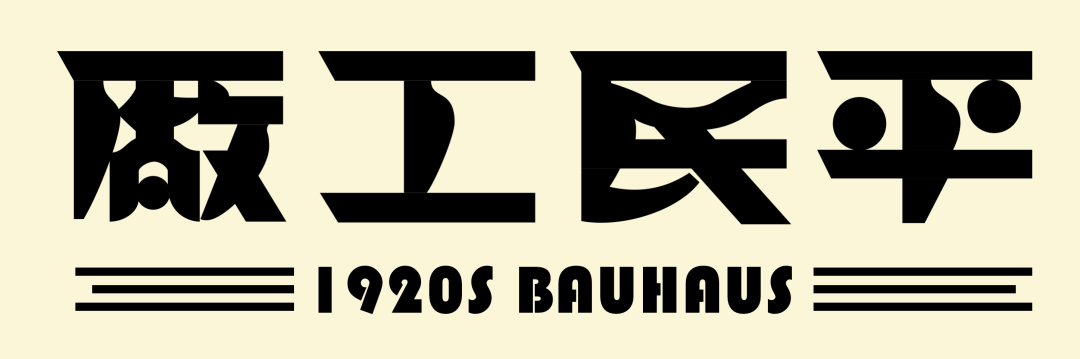
但是,后来由于历史的原因,“包豪斯”的设计观念没有在我国更广泛的普及,就这样中断了与世界文字美化的同步发展。
再到70年代末期改革开放以后,“平面”、“色彩”、“立体”三大构成的引进,也对现代美术字起了很大的推动作用。它使现代美术字冲破了几十年文字个体形象美化的局限,走上了现代设计的道路。
出于这种观念,后来不少美术学院和综合性院校的美术专业都将原来的“美术字”基础课目改成为“字体设计”,授课方式也由单纯的技法训练改革为设计基础的训练和设计思维观念的培养。
可是,说了半天,什么是现代美术字?现代美术字又是从哪里开始的呢?
简单来说,中国现代美术字是从十九世纪末和二十世纪初开始的。我们需要清楚这里的讨论范围,一定是中国的,且是现代的。
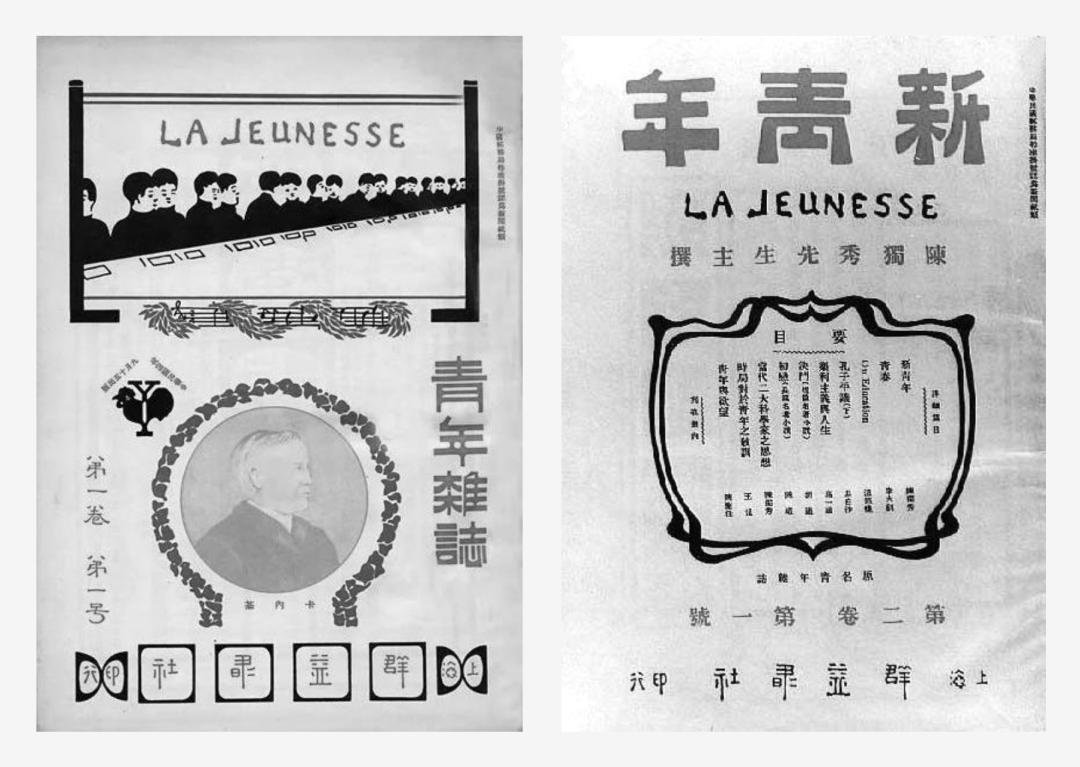
左:青年杂志(1915) 右:新青年(1916)
有人说,现代美术字体的使用是从陈独秀1915年创办的《新青年》才开始的,但是这并不准确。实际上现代意义上的中文“美术字”,在清末上海商务印书馆的一些出版物中就已经能够看到了。
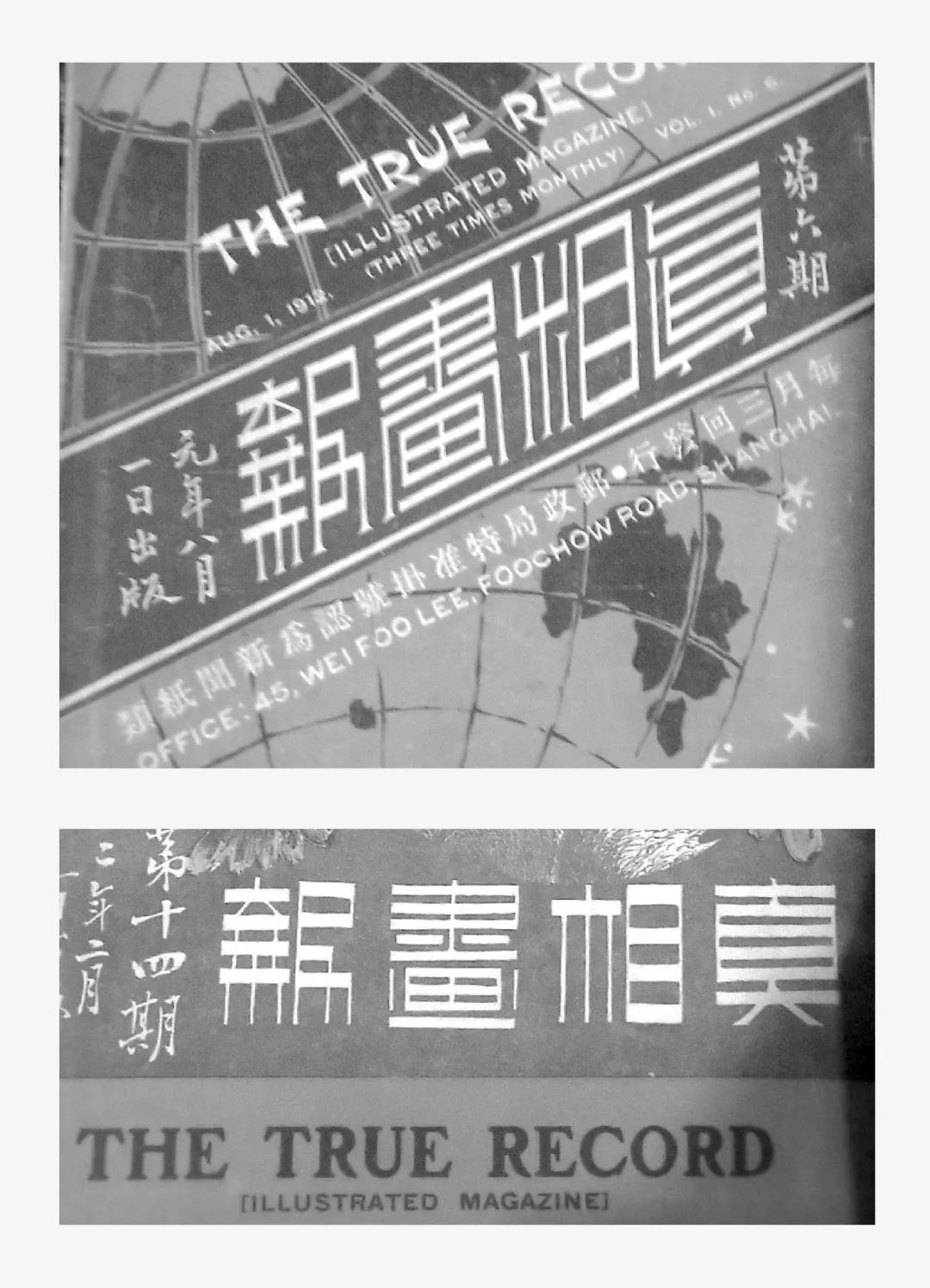
真相画报(1912 · 1913)
民国元年(1912年) 出版的《真相画报》第六期,1913年出版的《真相画报》第十四期,也都用了美术字。到20世纪30年代时,美术字的创作水平和使用的频率可以说都达到了顶峰。
19世纪末,西洋印刷技术的发展,让欧洲、美国的美术字异常繁荣,随着贸易和交流逐渐影响到了远东。而上海作为当时中国的第一个通商口岸,毫无疑问会接收到这样的影响。
维多利亚时期海报
而且当时又恰逢杂糅多元的维多利亚时代,我们看这里列举的几张图片就可见一斑了,各式各样形式的美术字可以说是层出不穷。不难想象,除了中国,这样的美术字大繁荣也直接影响到了刚刚打开国门的日本。
日本早期的图案文字
我们知道,19世纪下半叶的日本与鸦片战争后仍然保守的中国不一样,它虽然国门打开得比中国还要晚一些,但是很快就确立了“脱亚入欧”的国家战略,从各个领域全面向西方学习。所以,从明治时代开始日本就出现了“图案文字”,到大正时期已非常成熟。而这种知识也随着中日之间的交流被带到了中国。
当然,除了欧美、日本带来的影响这些外部因素,也一定还有内因。相信大家上初中时,政治课老师都会告诉我们:要找根本原因,就得从经济角度出发。
19世纪资本主义商品经济的发展中,中国的现代美术字在外国商业印刷品的影响下开始了萌芽。20世纪初开始,中国的民族工商业得到发展,在这个时期,发展最为迅速的是出版印刷业。
1897 年,我国历史上影响最大的民营出版机构——商务印书馆成立,在这之后,又有数家出版机构成立。这样民族出版业的发展,就加速了传统字体向现代美术字的转变,也促进了书籍装帧的产生。
我们知道文字是需要有一定的载体才能传播的,现代美术字也在这个时候赶上了许多新兴文字媒体的潮流。比如说存在于报纸、杂志、邮政、露天广告牌和电影中的广告媒体。这些广告在推动社会经济、文化发展的同时也带动了现代美术字的发展,它让讲究鲜明刺激的广告美术字走向了广阔的社会生活空间。
鲁迅为自己书而设计的美术字
除了广告,还有书籍装帧。而鲁迅先生正是这一艺术活动的先驱,他从1924年起指导培养了丰子恺、陶元庆等一大批青年装帧艺术家。并亲自动手绘制书籍封面和书名美术字。在鲁迅先生的倡导下,书籍封面成为现代美术字一个重要的表现媒体,从20年代以后一直反映着时代的审美特点。
画报也是现代美术字生存的温床。出版于1926年的《良友》 画报就是其中的代表,《良友》从内容版式到装帧设计都是当时的一流水平。而画报的兴旺让现代美术字在报头、刊图、标题字、广告文字等等方面有了施展的条件,使用量和品种也超过了其他的印刷品。实际上,二三十年代美术字专业书籍上的许多案例都是从画报上采辑的。
而公众宣传则是20世纪以来对现代美术字影响最大、应用最普及的一种文字媒介。它包含了室内外张贴、悬挂、散发的标语、宣传画、板报等一些非商业性文字宣传形式。公众宣传媒介比较重视文字大的宣传效果和艺术感染力,文字形体粗壮、醒目。它让现代美术字较早地进入了人们的社会生活,真实地反映着中国近现代历史的变革。
在现代美术字的诞生因素中,除了经济,还有教育因素。20世纪初我们就在学校中设置美术科目或是建立美术学校。在美术教育中开设图案教学课,让现代美术字能以新的造型理论加以阐释,并逐渐形成了系统的理论体系。可以说,现代美术字是依托着现代学校的新式艺术教育成长的。
而我国现代第一所国立的美术学校——北京美术学校(中央美术学院的前身)创立于1918年,最初就设有绘画和图案两科。其中字体设计就是图案法这门课的一部分。这部分内容在当时的教学体例中与“制版图案”(也就是今天所说的“平面设计”)密切相关。而这本由央美图书馆收藏的印于1919年的《现代美术字》就是一个明证。
现在我们大致了解了“现代美术字”的诞生因素,可是,这个称呼本身又是从何开始的呢?
实际上,“现代美术字”的名称,早在20世纪30年代初,我国出版的现代美术字专业书籍中已经作为书名使用。当然,在当时也有沿袭日本的叫法,称为“图案文字”的。
我们知道,实际上近现代中国通用的“图案”这个概念,就是来自于日本的。这个词是日本在参加1873年的维也纳万国博览会时,为了对应西方“Design”这个概念而创造的。
而从50年代到后来,我们基本上都叫“美术字”,或者加上前置词来限定它的范围,比如报刊美术字、变体美术字、宋体美术字等等,很少会再用图案文字来称呼了。
不过,就算提到所谓的“现代美术字”,我们通常也没有什么明确的概念,因为它的范畴真的十分宽泛,几乎包括了除传统书法和日常应用文字以外的所有经过装饰美化的文字。我们可以尝试把它们分为两类,以自由性格为特征的手绘美术字和以标准化、程式化为特征的印刷美术字。
手绘美术字里的“手”是手工书写的意思,而“绘” 有图绘、设计和借助工具绘制的含义。我们需要注意它与徒手书写的书法文字是不同的,也与日常应用的“手写体”有区别。之所以称它为“手绘”,是因为它比较符合这一类美术字的造型特点。
《非尘美术图案文字全集》1933
比如我们来看这个旧版字集中的案例,就是明显的手绘美术字。不过值得一提的是,实际上在以前哪怕是很规矩的宋体黑体,都会先由手绘而成,这是现在许多设计师比较缺乏的一块。
而在当时手绘美术字的主要应用媒介有两种形式,一是应用在印刷纸面上,比如报刊、书籍等等;另一种则是应用在其他形式和材料上,比如说室外的广告牌、店面的匾额等等。
方正宋黑体 最初原创者——徐学成
而印刷美术字是现代美术字的另一大系统,主要指现代印刷技术兴起以后的成套成系列的专供印刷使用的文字。
印刷美术字的特点是标准、规范、程式化强,能满足社会各阶层人们的审美需要。得益于稳定性,重复使用和批量生产是它的工艺特点。我国印刷美术字以宋体、黑体、仿宋体为主。至于印刷文字中的楷书、隶书、行书和其他手写文字,因为本身没有经过装饰美化,所以不属于印刷美术字的范畴。
不过到了现在的电子荧幕时代,完成一款字体大多数时候都靠计算机完成,已经不属于刚才所讲的分类定义范围内了。现在,相信大家都对美术字已经有了一个初步的了解了,接下来我将跟大家细说一下现代美术字的发展历史,和它在不同时期下的主流形式变化。了解这些后,最直观的作用就是能拓宽我们的做字思路,学习到更多的变化可能性。
第一阶段:从萌芽到成熟
1900s — 1930s
我们知道,汉字的发展历史悠久,主流字体发生过很多的变化,只不过彼时的变化都是万变不离其宗,这里的宗指的就是汉字是由线构成的本质。
而之前我们也讲到了,在20世纪初期我国就受到了现代艺术影响。特别是20年代后期以后,伴随这大批留欧艺术家回国,各种具有装饰艺术、结构主义风格的现代美术字出现了。受这些新观念的影响,我国汉字由传统的线结构向以点、线、面为特征的量块体积结构转变。